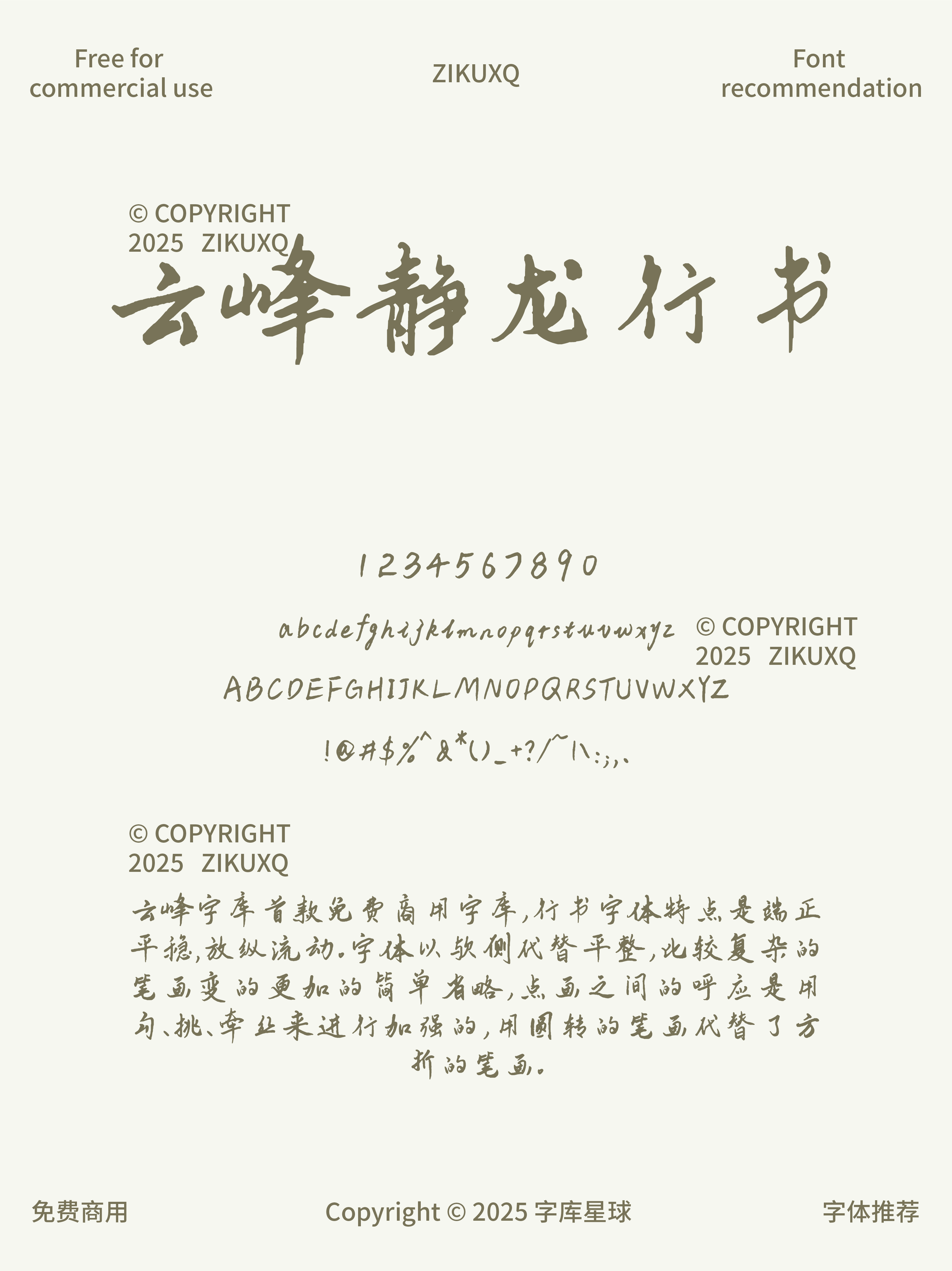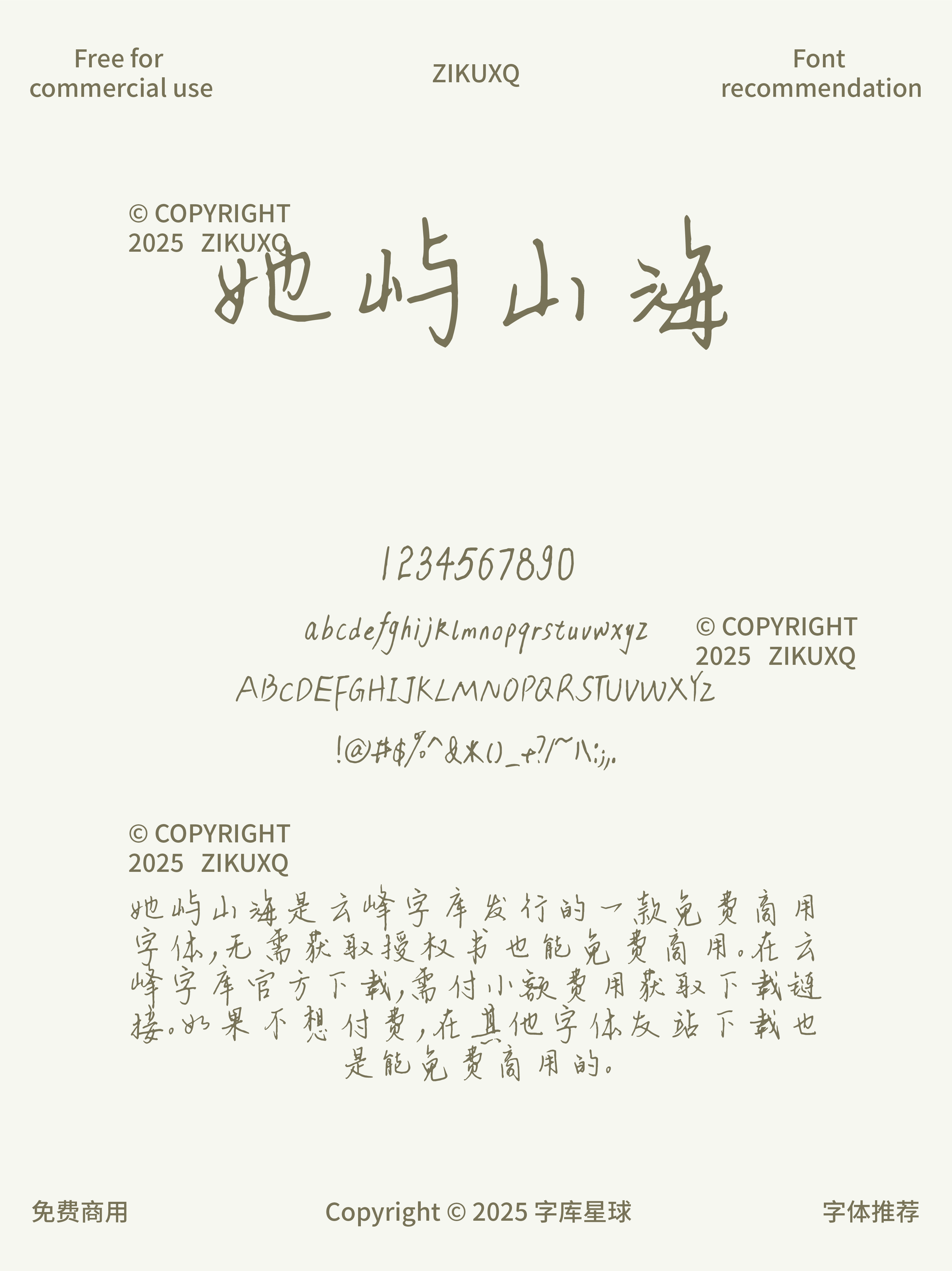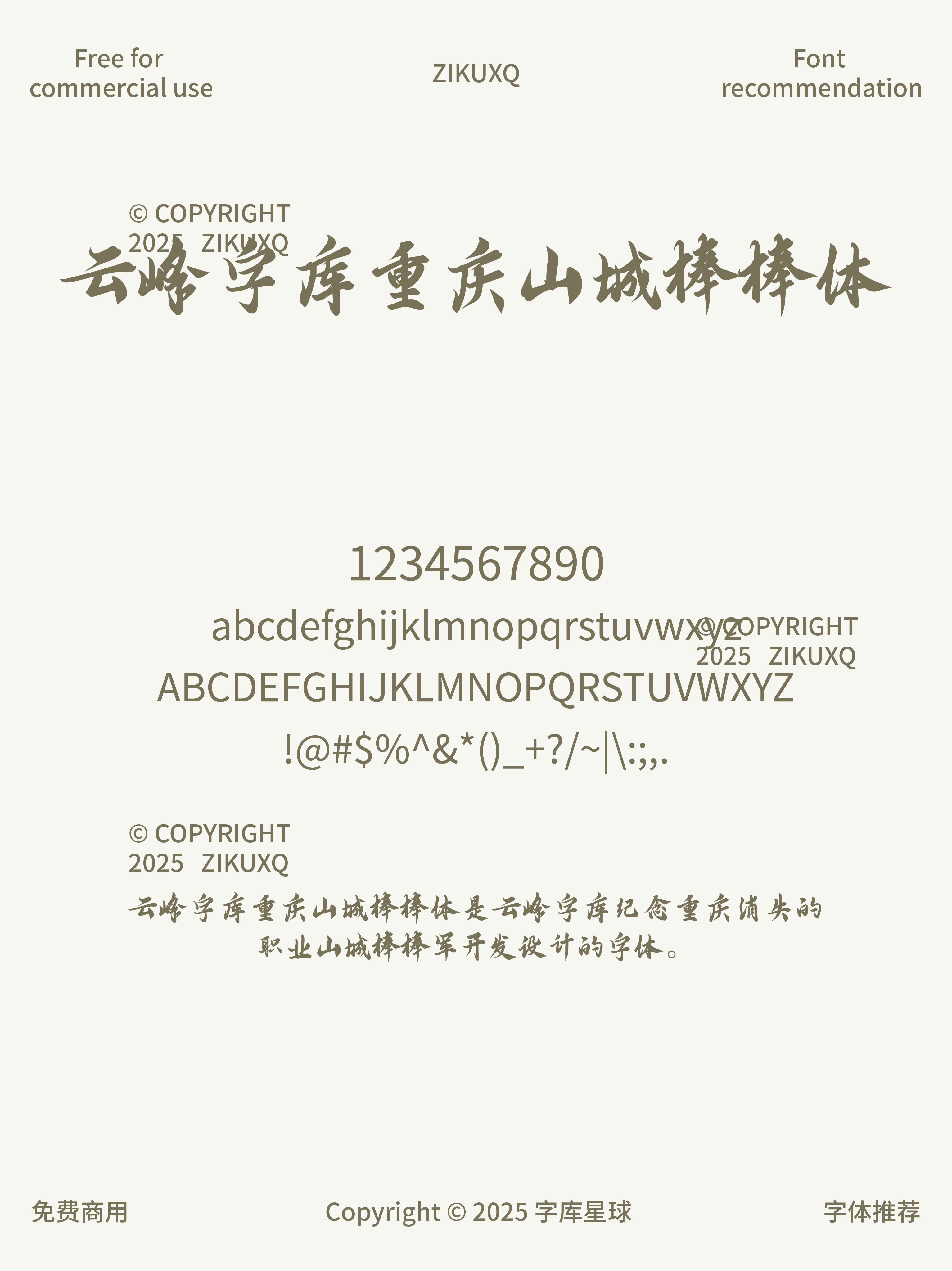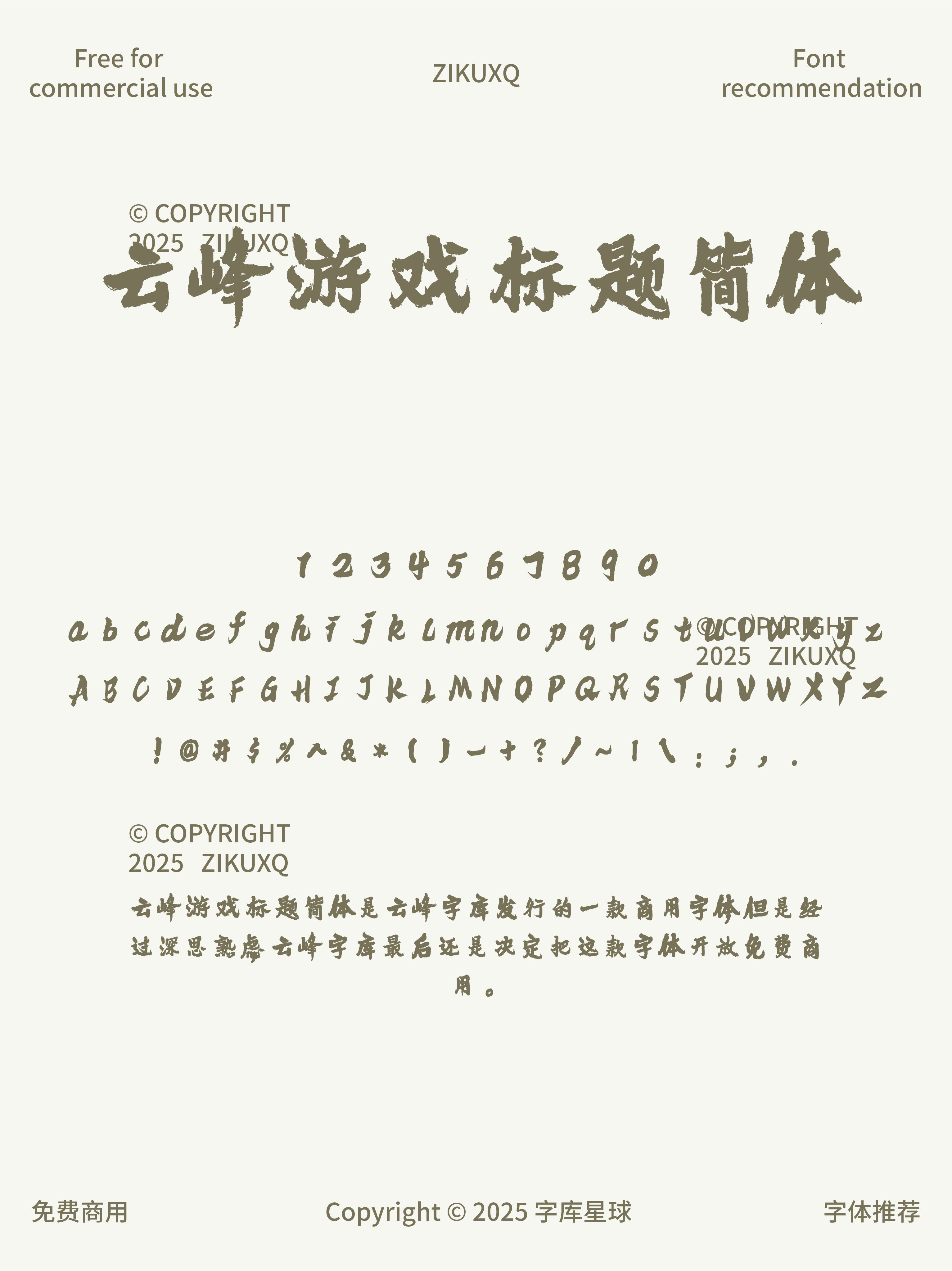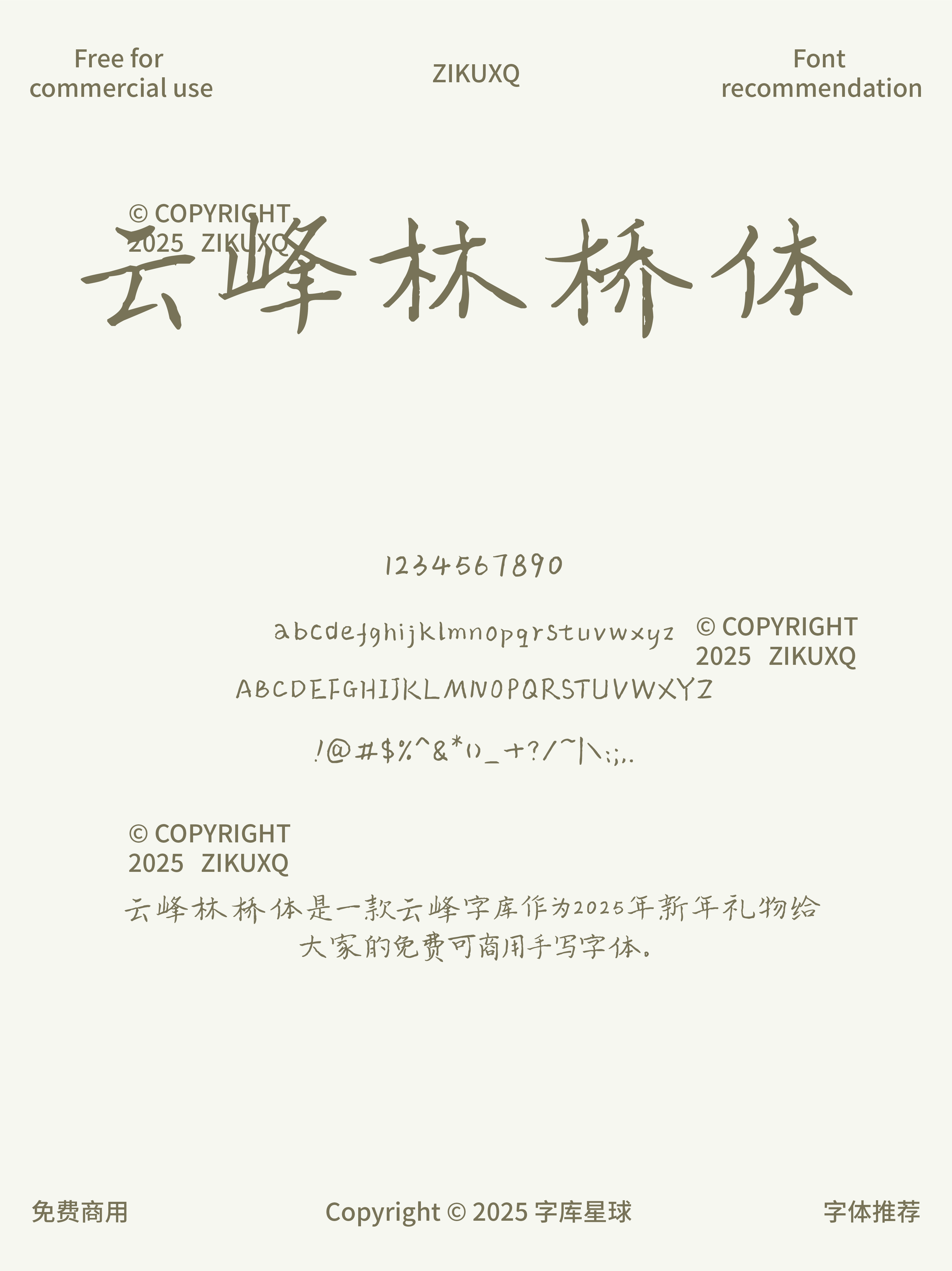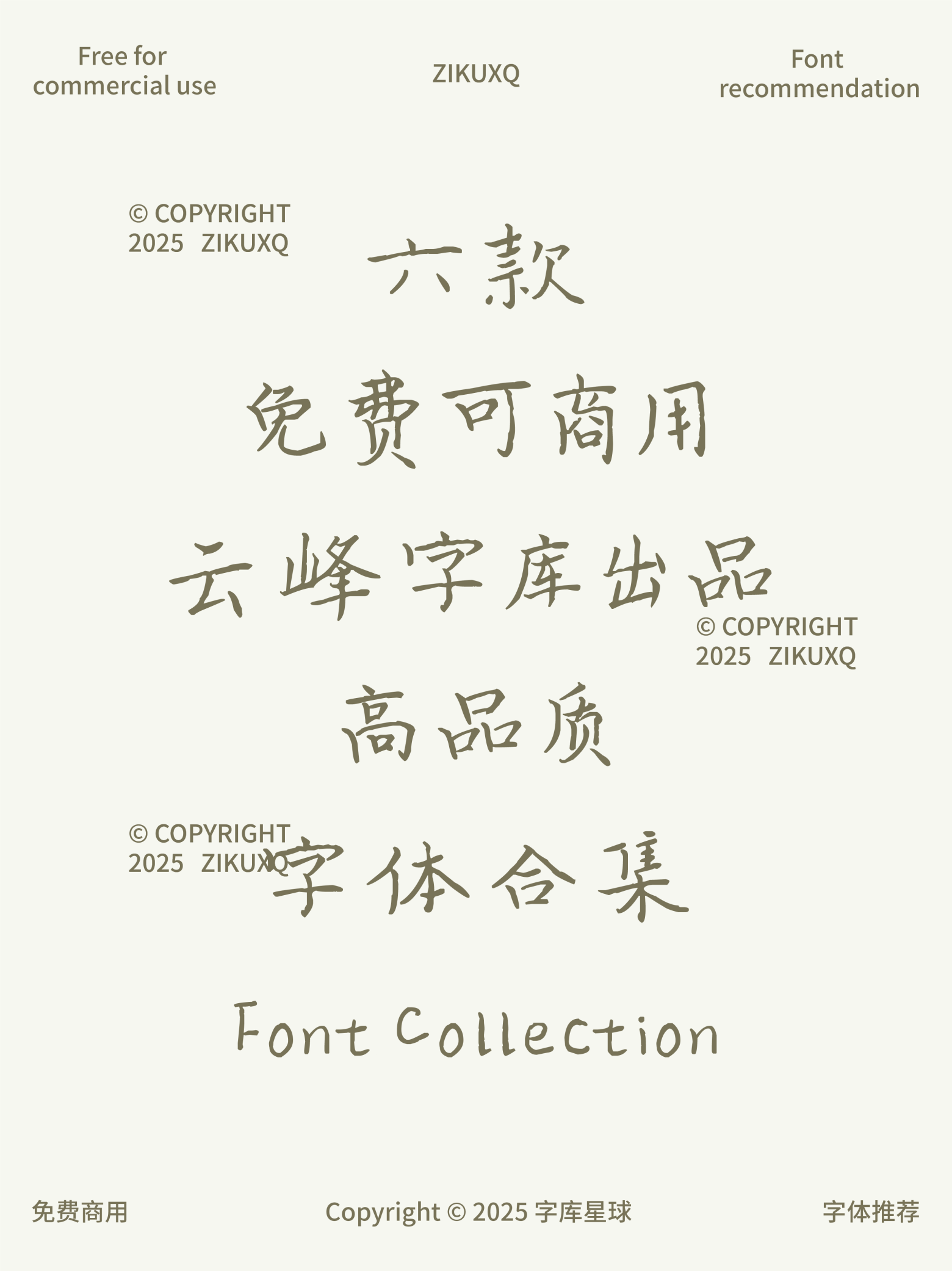
六款免费可商用云峰字库出品设计的字体
今天给大家分享 6 款超实用的免费可商用字体,来自云峰字库。在设计中,字体的选择至关重要,合适的字体能让作品瞬间提升档次,而这 6 款字体绝对能满足你的各种需求!
手写风格的标题字体,视觉冲击力超强。字体笔画豪放大气,充满力量感,特别适合用在游戏、影视、广告等需要快速吸引眼球的场景。比如游戏宣传海报,用这款字体做标题,一下子就能抓住玩家的注意力。
字体风格飘逸灵动,笔画流畅自然,仿佛带着一种自由的气息。在一些文艺、浪漫主题的设计中,如书籍封面、文创产品包装等,它能营造出独特的氛围,让整个设计更具诗意和艺术感。
行云流水般的行书字体,兼具书法的韵味和美感。它的笔触细腻,线条富有变化,非常适合用于传统风格的设计,像中式餐厅的菜单、古典风格的海报等,能展现出浓厚的文化底蕴。